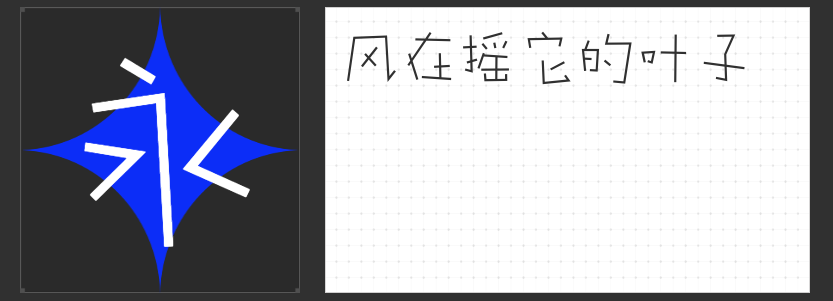
四款创意字体为你的短视频增添独特魅力🤑
在短视频创作中,字体的选择是提升视觉吸引力和传达情感的关键。今天,我们为大家推荐四款适用于短视频的字体,它们风格各异,能够为你的视频内容增添独特的视觉表现力和情感共鸣。
1. 字恋狂风摇简 常规
“草在结它的种子,风在摇它的叶子。”字恋狂风摇简 常规 是一款充满温暖气息的字体,其笔画摇摇晃晃、歪歪扭扭,仿佛被风吹过一般,充满了手写的自然感。字体的比例故意设计得失衡夸张,给人一种随性而又不失美感的感觉。这款字体非常适合用于短视频中的文艺风、治愈系或情感类内容,能够为画面增添一份温暖与灵动,让观众感受到文字背后的情感力量。
2. 励字可变志向黑简
励字可变志向黑简 是一款融合了圆体与黑体特点的字体,其笔画拐角增加了适当的外圆角处理,在稳重大气的字形中增添了一丝灵动感。字体的字面充实,结构稳定,非常适合用于短视频中的标题、字幕或信息展示部分。无论是科技类、知识分享类还是商业类短视频,这款字体都能为你的内容增添一份专业与时尚感,同时确保文字在屏幕上清晰易读。
3. 励字雪花特效简
励字雪花特效简 是一款极具视觉表现力的字体,其字型饱满方正,粗度夸张,内部加入了大小不一的圆形元素,对角线做了圆角处理,呈现出独特的雪花感。字体中的圆点分布均匀,大小错落有致,让整体字形更加突出。这款字体非常适合用于短视频中的节日主题、冬季场景或需要强烈视觉冲击的内容。它能够为你的视频增添一份趣味性和节日氛围,吸引观众的注意力。
4. 字恋狂丸粒简
字恋狂丸粒简 是一款可爱风格的字体,其笔画圆头圆尾,转折处加入了圆角处理,整体字形圆润饱满,富有亲和力。这款字体非常适合用于短视频中的萌系、儿童内容或轻松搞笑类视频。它能够为你的视频增添一份俏皮与活力,让观众感受到轻松愉快的氛围。无论是表情包字幕、动画解说还是生活记录,字恋狂丸粒简都能为你的内容增色不少。